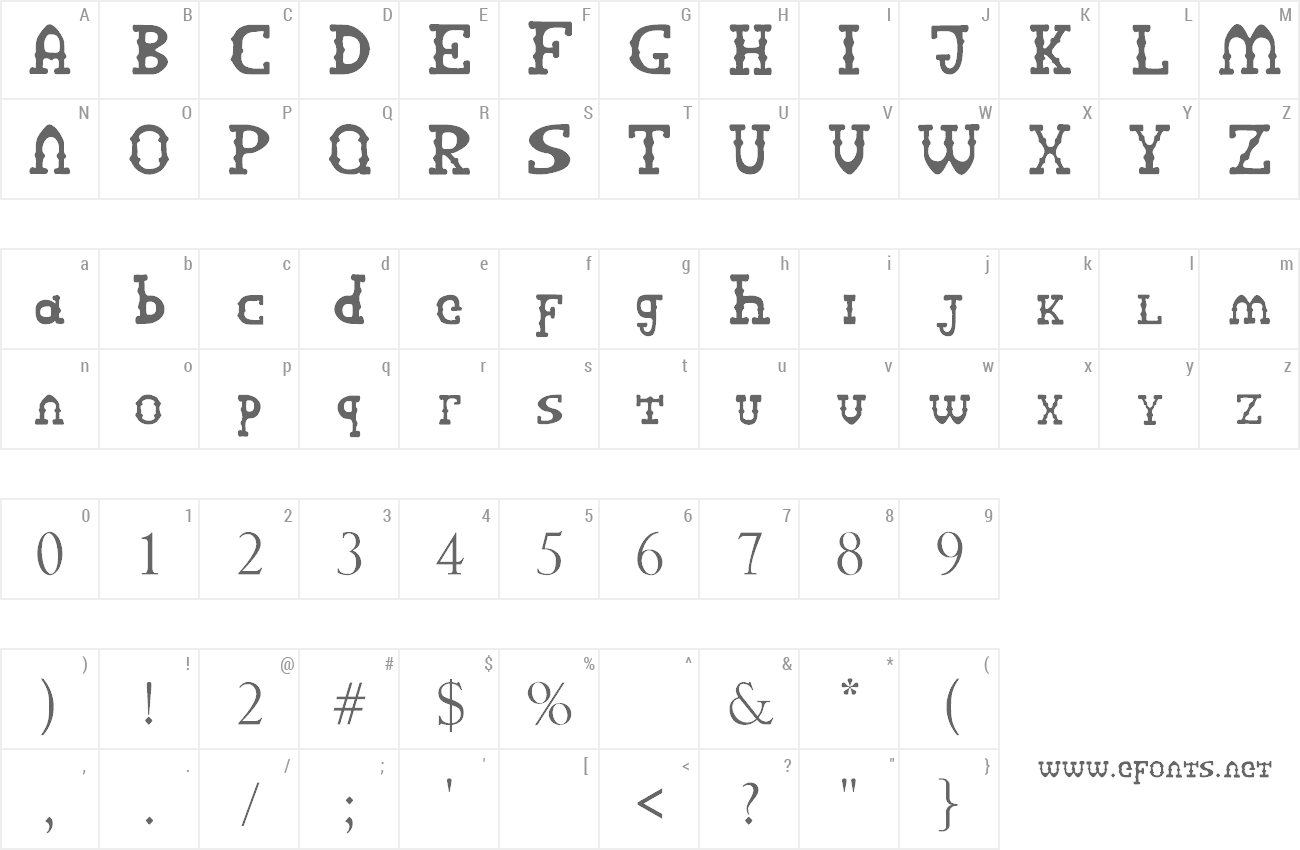
| Font name: | Arcutype SV |
| Author: | Kevin Salinas |
| Note by Kevin Salinas | |
Tipografía creada como examen parcial de la materia tipografía aplicada en la carrera de diseño gráfico por el alumno Kevin Salinas. Tipografía basada en la arquitectura salvadoreña, pero más que todo en el uso de arcos de medio punto y ojivales, a la vez reflejando un poco de la cultura y la arquitectura del gran San Salvador. Kevin Salinas Diseñador Gráfico |